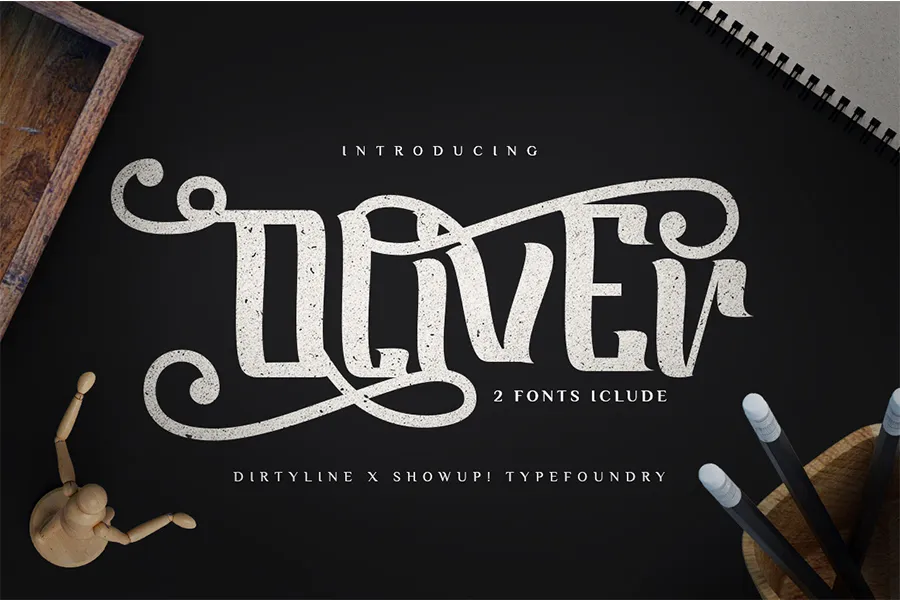
Oliver Typeface – Fonte Grátis
Oliver Typeface
Oliver Typeface é uma elegante e única escolha para qualquer projeto design que deseje destacar-se. Perfeita para aplicações variadas como panfletos, logotipos, camisetas, sinalização, cartões de visitas, revistas, capas de livros, convites de casamento e cartões de boas-vindas, esta fonte vem pronto para fazer um impacto em qualquer design. Sujeito ao talento elegante e único de Hamilton, a Oliver está aqui para adicionar um toque distintivo às suas criações. Com seu design sólido e arredondado, esta fonte é perfeita tanto para estilos tradicionais quanto modernos, tornando-a uma escolha versátil que combina facilmente com qualquer projeto visual.